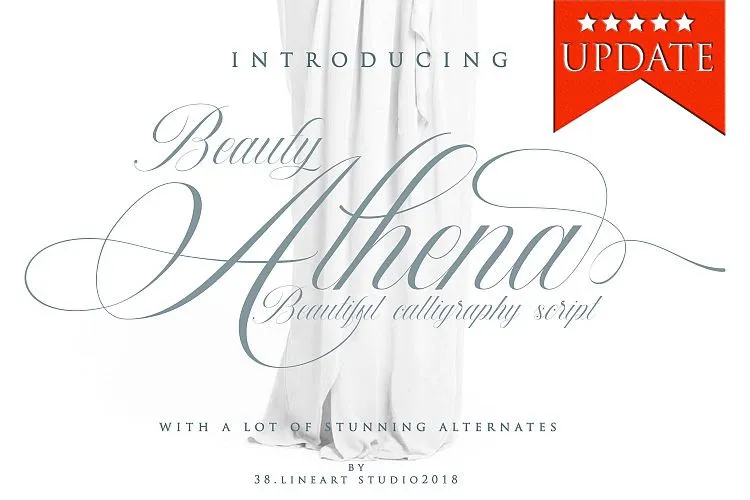
Beauty Athena Calligraphy Font – Download Grátis
Olá amigos! Este é um fonte de calligrafia moderna com acréscimos contemporâneos e sofisticados. É perfeito para marcas e identidades de negócios, convites de casamento e cartões, talvez até mesmo etiquetas de vinho vermelho. Introduzindo a fonte Beauty Athena. Athena é uma deusa da sabedoria, coragem, inspiração, matemática, força, estratégia, arte, artesanato e habilidade. A fonte Athena vem com caracteres muito bonitos que mudam. É um tipo de script ornamental cromado clássico com toques modernos, projetado com detalhes altos para criar elegância estilizada, simplicidade, feminilidade sensual, glamour e uma leitura limpa e fácil. Com tantas conexões entre as letras, é perfeito tanto para usar sozinha quanto quando combinada em conjuntos de texto.